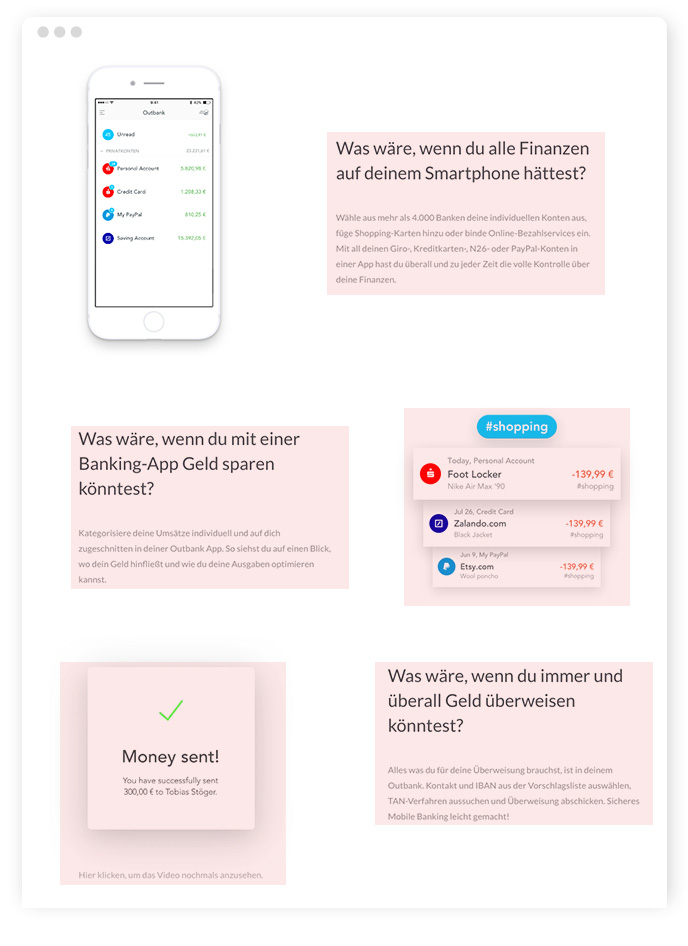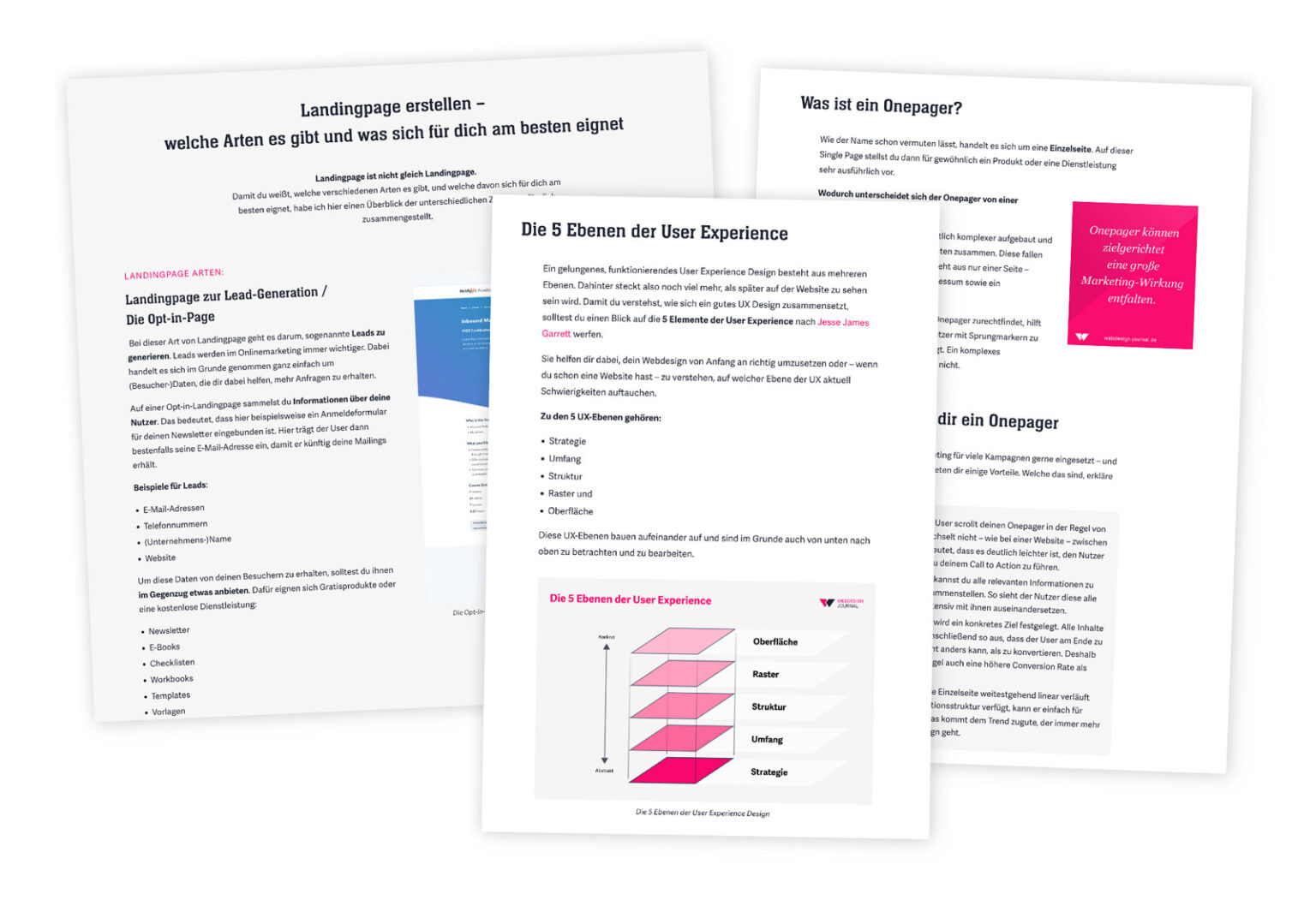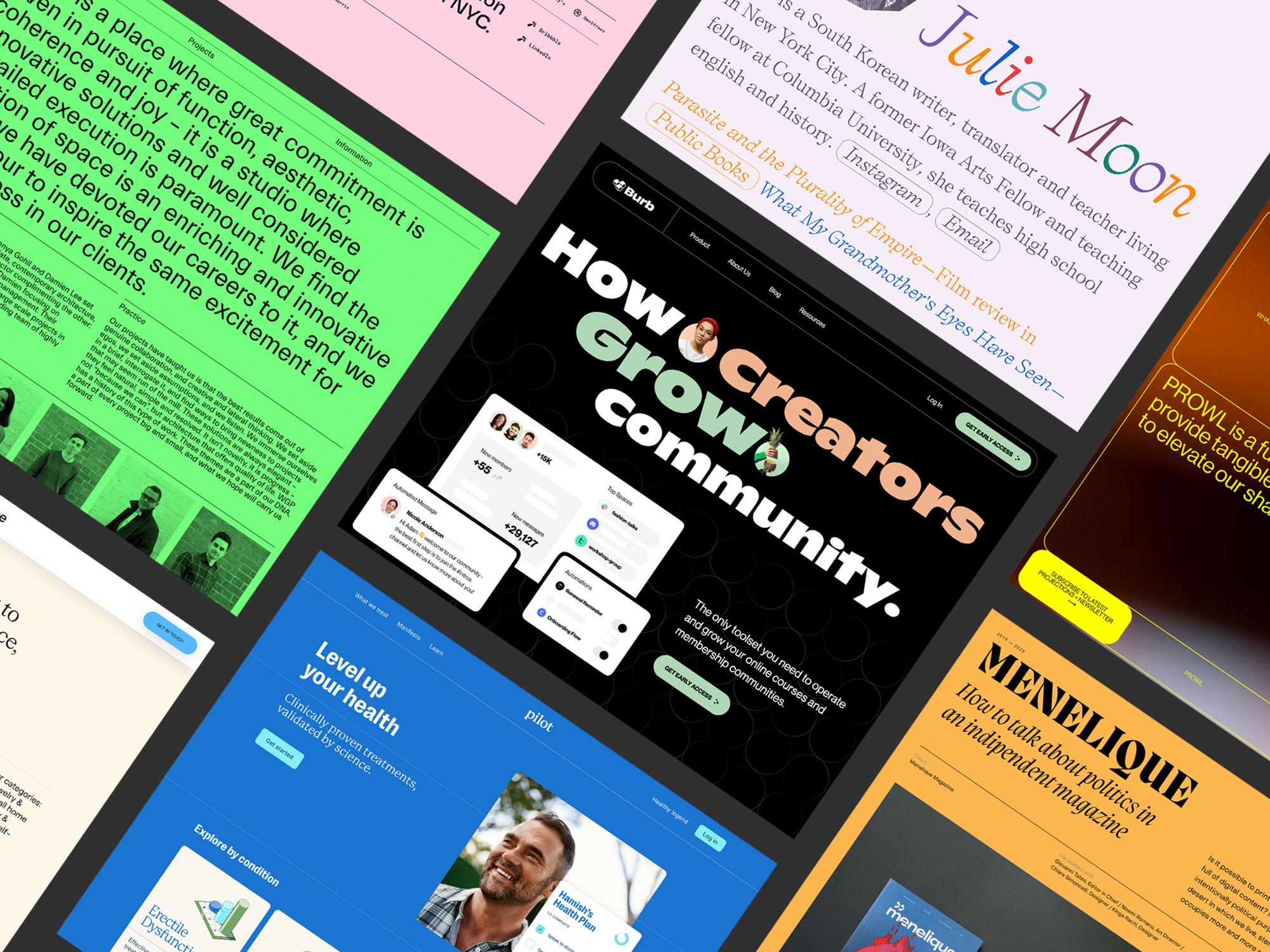
Die ultimative Anleitung 2026
Typografie verstehen
& gestalten
Content is King und die typografische Gestaltung sorgt dafür, dass dieser überhaupt erst gut aufgenommen werden kann.
Lerne in diesem Artikel wie du Text gestaltest, die eine Wirkung entfalten und gut lesbar sind.
Nicht selten, dass die Typografie zu wenig beachtet wird. Templates, CMS-Themes und Frontend-Frameworks liefern oft schon eine gute Basis-Gestaltung – und dabei bleibt es dann meistens. Eventuell werden noch die Schriftarten ausgewählt, fertig. Verschenktes Potential, denn es geht um die Inhalte, die meistens in Textform vorliegen, und damit eben auch um die Textgestaltung.
Um effektiv Texte zu gestalten, solltest du die typografischen und technischen (CSS-)Möglichkeiten kennen.
Die Gestaltung des Textes soll die inhaltliche Aussage des Textes visuell transportieren. Ein Gefühl vermiteln. Die Gestaltung des Textes soll eine visuelle Hierarchie schaffen, sie ist die Benutzerschnittstelle, sie gestaltet das User Interface, sie kreiert die User Experience.
Auf dieser Seite verschaffe ich dir einen Überblick, was typografische Gestaltung bedeutet, was du beachten solltest, mit welchen CSS-Eigenschaften du deine Texte beeinflussen kannst samt jeder Menge Best Practice-Beispiele. Los gehts…
Folgende Infos wirst du in diesem Typografie-Artikel bekommen: Danach weißt du, was du zu tun hast und kannst alle Schritte direkt umsetzen.
Was bedeutet gute Typografie und warum ist sie so wichtig?
Ein guter Webdesigner muss sich intensiv mit der Gestaltung von schriftlichen Informationen auseinandersetzen, also mit der sogenannten Typografie. Gute Typografie sorgt für eine gute Lesbarkeit. Der Leser kann sich auf den Inhalt konzentrieren und nicht  auf die Formatierung.
Gute Typografie wirkt aber auch emotional. Sie beeinflusst, wie Inhalte verstanden und wahrgenommen werden. Sie unterstützt den Inhalt in seiner Aussage. Im Idealfall trifft sie den richtigen »Schrift«-Ton. Dabei ist Typografie ein Handwerk mit dem Ziel, Sprache sichtbar zu machen. Meistens dreht es sich aber mehr darum, was geschrieben wird, als darum, wie es geschrieben wird. Und, was eigentlich am wichtigsten ist, wie es andere lesen. Text lässt sich hierbei im Grunde wie ein User Interface betrachten.
Texte sollten so gestaltet sein, dass sie den Blickverlauf lenken, Aufmerksamkeit an der richtigen Stelle erzeugen und die Informationen schnell aufgenommen werden können.
Typografie geht daher über die Auswahl passender Schriftarten weit hinaus.
So sollte Webtypografie nicht sein:
Alles wirkt wie eine Textwüste.
Moderne Webtypografie im Einsatz
Typografie-Branding für Automarken
Vergleichen Sie die oberen Headlines der Websites von deutschen Automobilherstellern. Erkennen Sie die Unternehmen wieder?
Und was für eine visuelle Aussage bzw. welches Image wird jeweils vermittelt?
Schriftgröße und -farbe, Zeilenlänge und -abstand spielen ebenso eine Rolle wie die Strukturierung des Textes in Überschriften, Absätzen, Aufzählungen und so weiter. Text fungiert also als Benutzerschnittstelle zwischen dem Anwender, der ein Bedürfnis befriedigen möchte, und dem Websitebetreiber, der ein Ziel verfolgt.
Ebenso wie ein Logo, die Farben oder Bilderwelten unterstützt Typografie die Wiedererkennung eines Unternehmens. Die Identität, das gewünschte Image eines Unternehmens kann und sollte auch mit Typografie ausgedrückt werden.
Feste Regeln für gute Typografie gibt es nicht. Allein die Definition »gut« ist schwierig. Typografie ist kein mathematisches Problem mit nur einer Antwortmöglichkeit. Nicht jeder Leser wird den Text auf die gleiche Weise interpretieren. So gibt es immer verschiedene »Lösungen«. Immerhin existieren Richtlinien und Best Practices, an denen man sich durchaus orientieren kann. Die wichtigsten stelle ich in diesem Artikel vor. Gute Typografie heißt also auch, sich mit den Inhalten auseinanderzuetzen und deren Bedeutung und Ziele zu verstehen.
Der Lesevorgang
Beim Lesen lernen muss noch jeder einzelne Buchstabe erkannt und gelesen werden. Geübte Leser müssen aber nicht mehr jeden einzelnen Buchstaben lesen, sondern erkennen eher sogenannte Wortbilder:
Für ganze Wörter hat sich so jeweils ein Wortbild eingeprägt, das wir schnell wiedererkennen können. Wir merken das, wenn wir Fremdsprachen oder generell seltene, ungewöhnliche Wörter lesen müssen. Dies dauert entsprechend länger, da wir genauer hinschauen müssen (und manchmal eben doch wieder jeden Buchstaben einzeln lesen müssen).
Beim Lesen springt das Auge die Zeilen in mehreren Schritten ab, ca. 5 bis 10 Buchstaben, was 1 bis 2 Wörter entspricht. Während der Bewegung sieht das Auge nichts, erst beim Stillstand werden Wortbilder erkannt.
Das Auge springt beim Lesen von Wortbild zu Wortbild.
Diese Erkenntnisse sind insofern wichtig, dass die typgrafische Gestaltung das Erkennen dieser Wortbilder vereinfacht. Oder andersherum ausgedrückt: